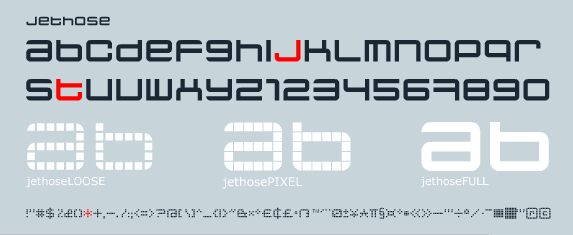
Jethose Loose von www.transporter.at ist eine kostenlose digitale Display-Schrift, die jeden Buchstaben in eine Anordnung aus kleinen schwarzen Kacheln verwandelt. Jedes Zeichen besteht aus strengen quadratischen Modulen, die jedoch in weiche, abgerundete Ecken übergehen. Das Ergebnis ist eine faszinierende Mischung aus Pixel-Strenge und der fließenden Ästhetik von Neon-Schriftzügen. Der Look erinnert an eine Retro-LED-Anzeigetafel, die so weit vergrößert wurde, dass sie auf dem Bildschirm oder im Druck fett, haptisch und unverwechselbar wirkt.
Mit Jethose Loose wirken Ihre Texte wie eine Systemanzeige von einem vergessenen Spielautomaten. Damit glänzt die Schrift besonders auf Sci-Fi-Postern, Techno-Flyern, Spieletiteln, Album-Artworks, Motion Graphics und experimentellen Website-Überschriften. Diese kostenlose Schrift überzeugt in großen Größen und lässt sich hervorragend mit einer geometrischen serifenlosen Schrift für den Fließtext kombinieren, um das Layout lesbar und scharf zu halten.